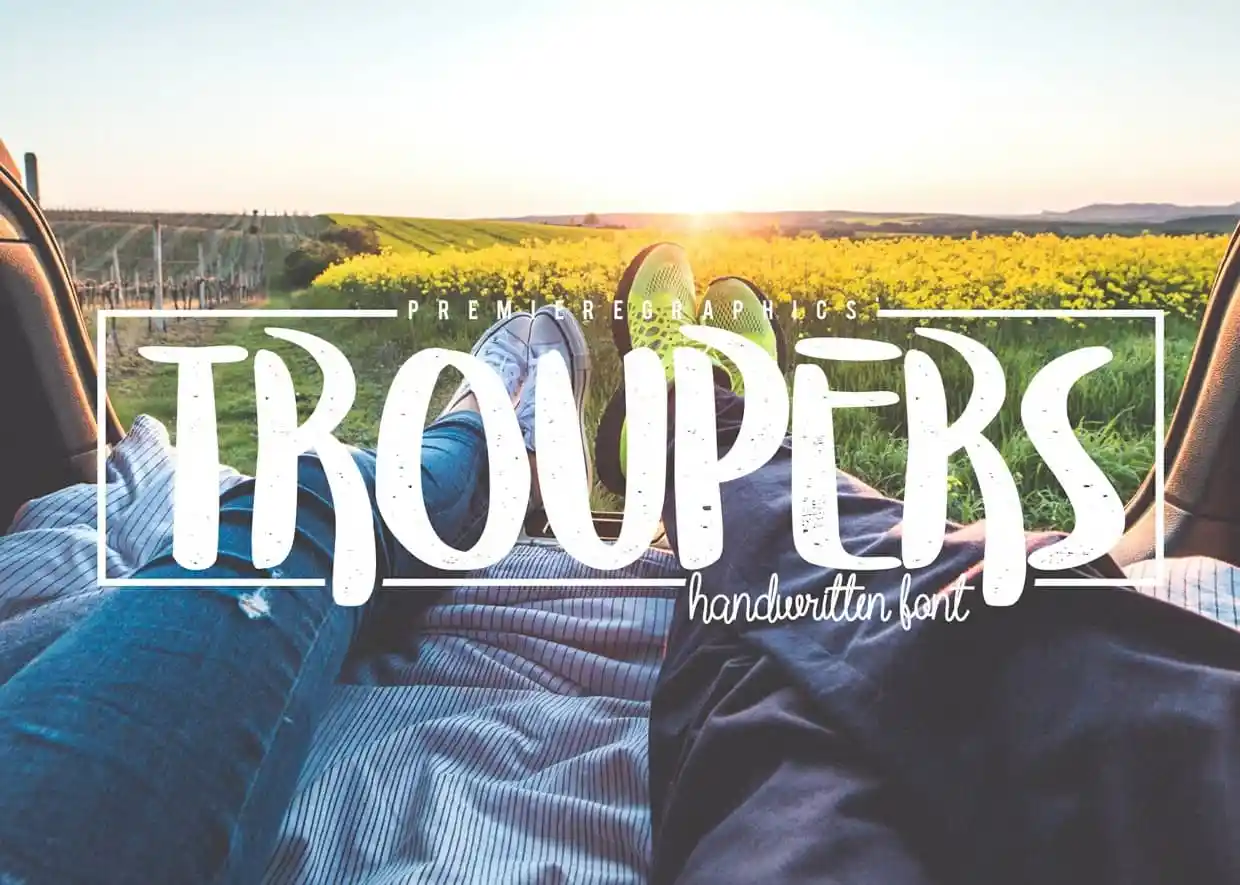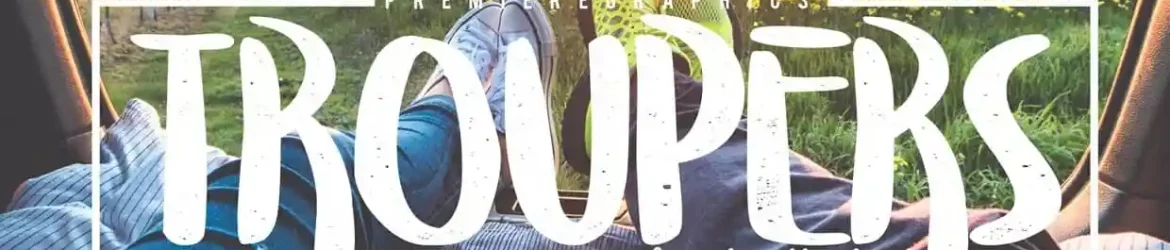
Troupers Font – Download Grátis
Introduzimos Troupers Font! Desenhado e compartilhado pela PremiereGraphics, Troupers é uma fonte cuidadosamente escrita para dar a sensação de descontração e leitura fácil ao seu design gráfico. Ideal para logotipos, fotografia, embalagens, identidades corporativas, anúncios e qualquer outro tipo de design gráfico que possa imaginar, Troupers é uma solução perfeita para tornar o seu trabalho ainda mais agradável e criativo. Com um tom levemente divertido e cheio de vida, esta fonte é perfeitamente adaptada para dar um toque pessoal e único a qualquer projeto. Seja você um designer gráfico ou simplesmente alguém que quer enfeitar suas próprias mensagens com uma fonte única, Troupers está aqui para oferecer a solução perfeita. Não hesite em experimentar o poder do Troupers em seus projetos e veja como ele pode transformar sua identidade visual de maneira encantadora.